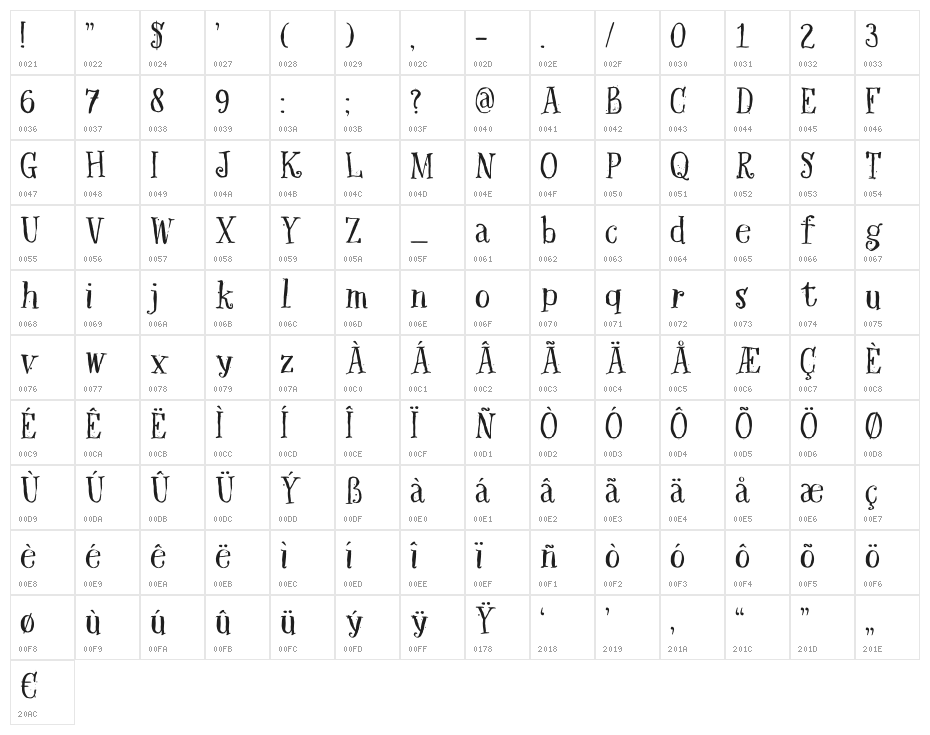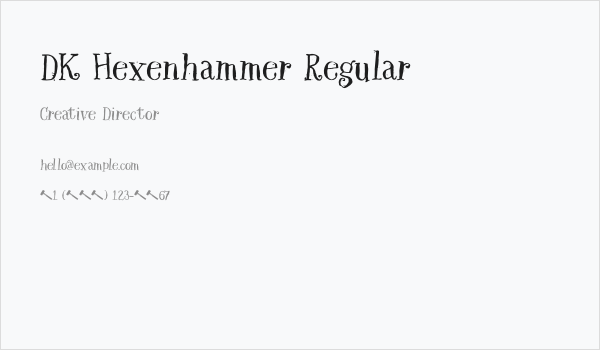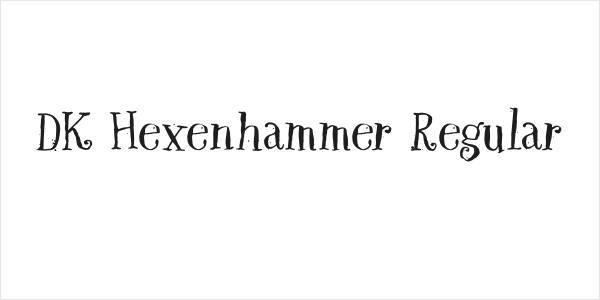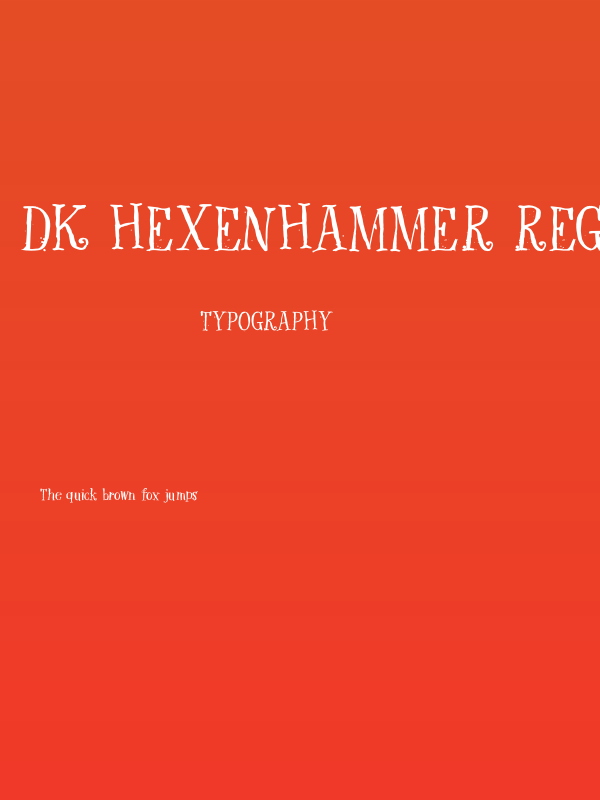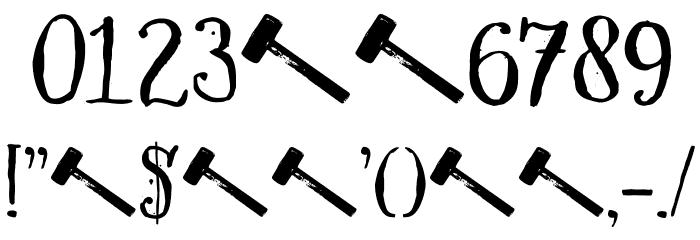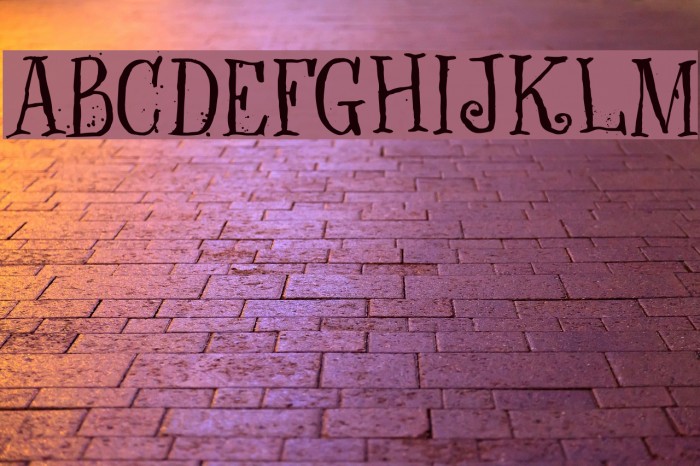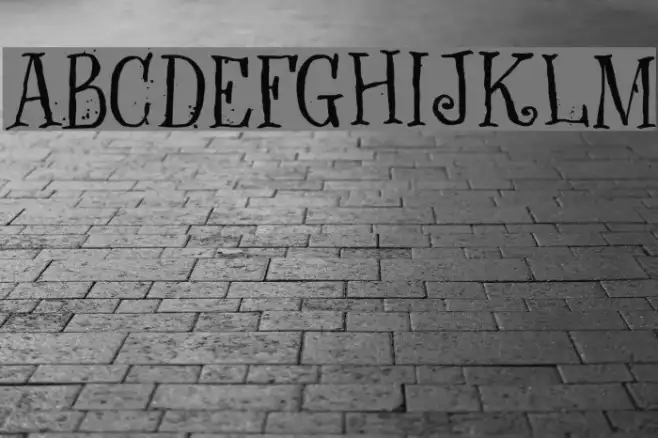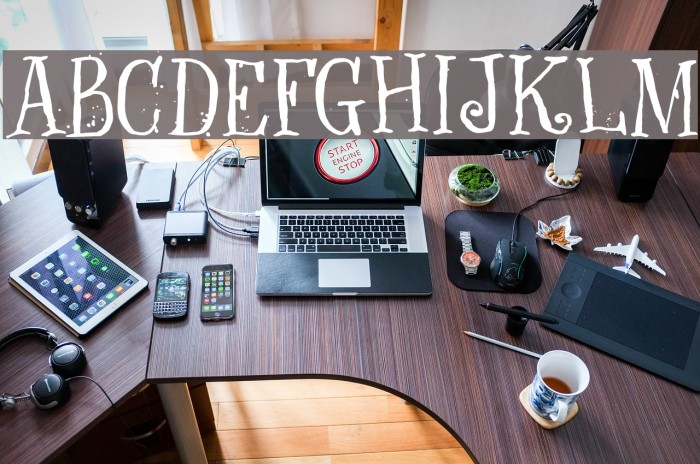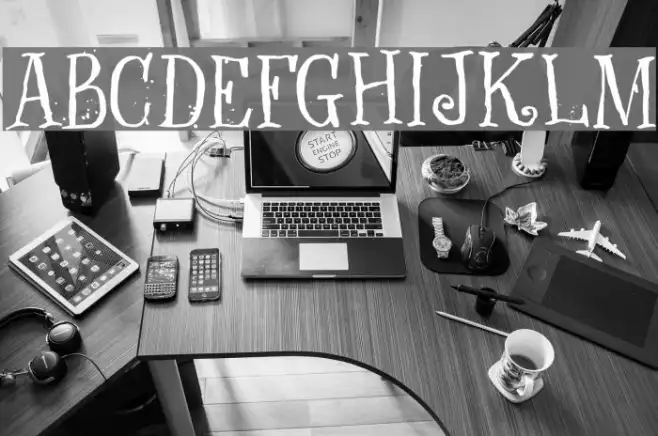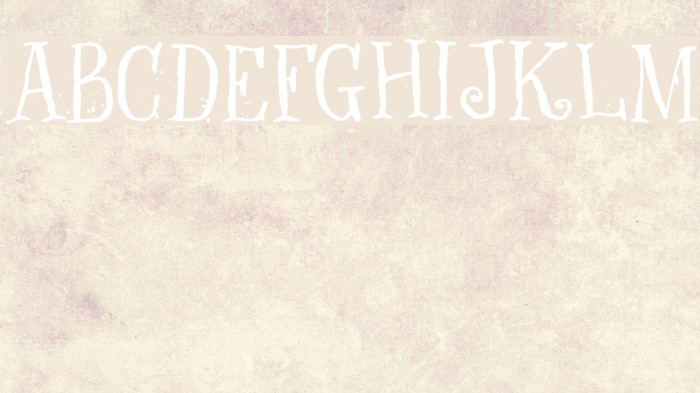
DK Hexenhammer Regular Font
| Estilo general | Vintage |
| Caso de uso | Headlines, Logos, Artistic projects |
| Proyectos propuestos | Ideal for vintage posters, historical themed events, rustic branding, and artistic projects requiring a distressed look. |